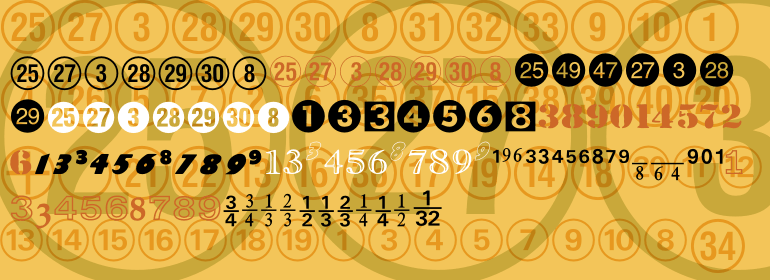
Numerics
Numerics,这款字体结构工整、笔画清晰,兼顾美观与易读性,适用于标题、正文、海报、包装、LOGO 等多种场景。字形优雅稳定,风格百搭耐看,适配日常排版与创意设计,让文字呈现更舒适、更具质感。Numerics一笔一画,皆是细节,以均衡的比例、流畅的线条打造舒适视觉体验,字形端正大气,风格简约现代。无论是商业设计、品牌宣传还是日常排版,都能轻松驾驭,让文字更有格调与力量。Numerics字体下载。